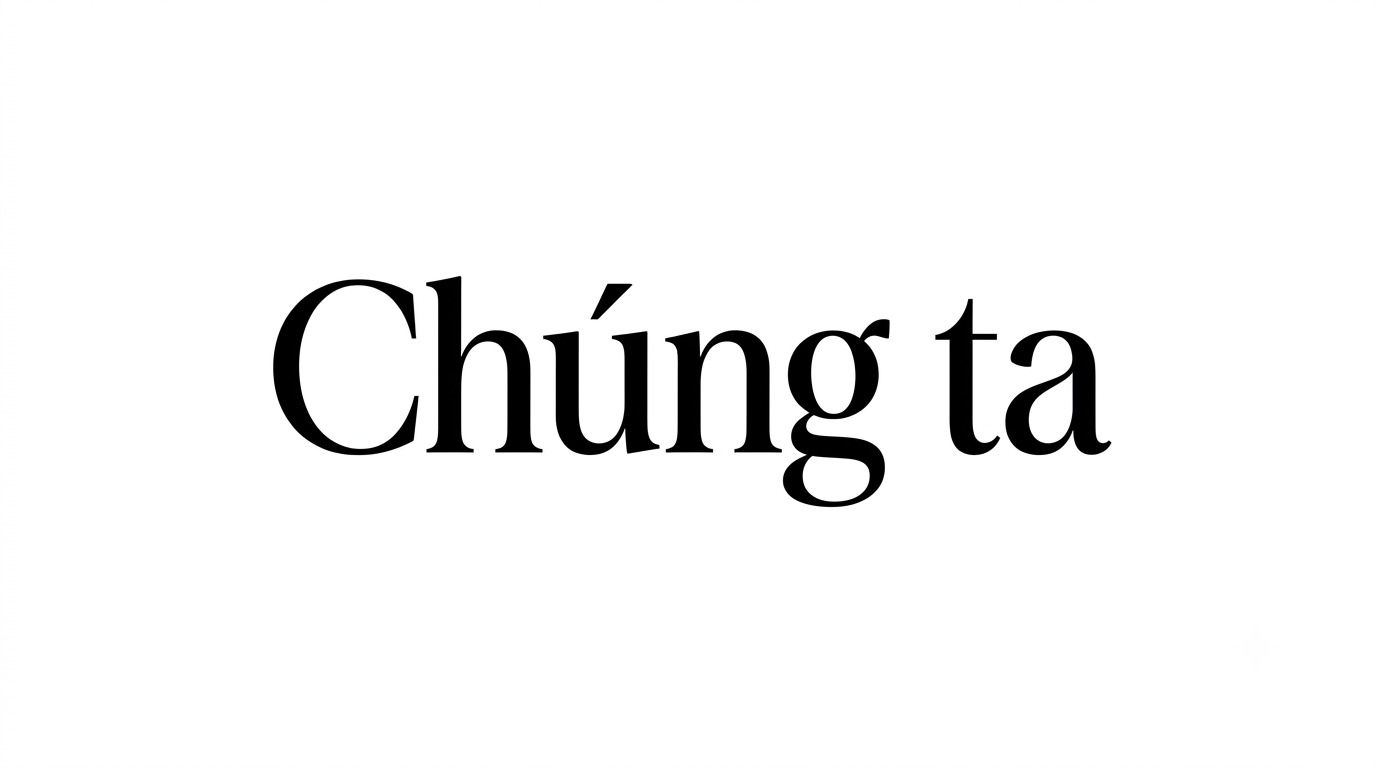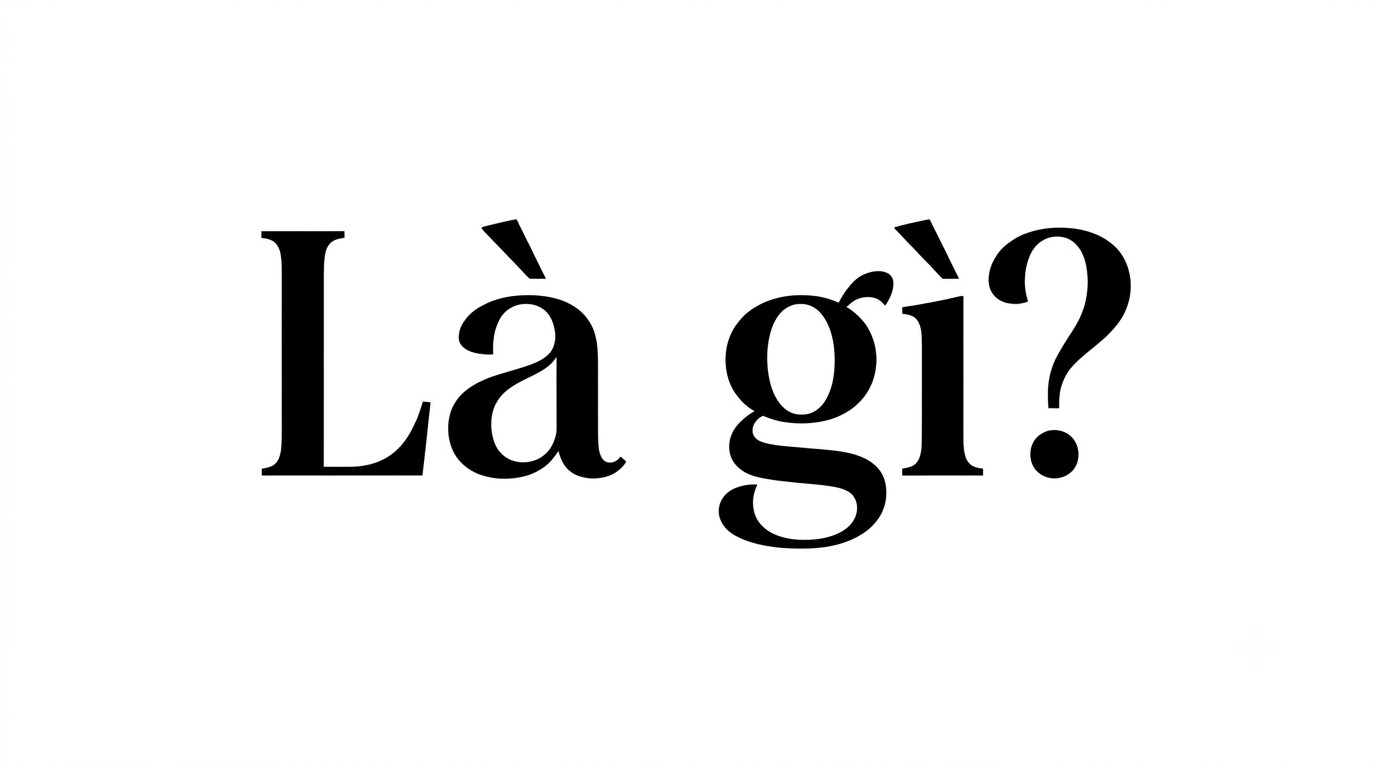
Tải 10+ bộ font Việt hóa Boxroom sắc nét chuyên cho thiết kế thương hiệu hiện đại
Nhiều nhà thiết kế yêu thích phong cách tối giản của Boxroom nhưng thường gặp lỗi font bị thiếu dấu tiếng Việt, sai ký tự hoặc đường path bị vỡ khi phóng lớn để in ấn hộp quà cao cấp. Những lỗi kỹ thuật này có thể làm giảm độ sắc nét của thiết kế, ảnh hưởng đến hình ảnh chuyên nghiệp và giá trị cảm nhận của thương hiệu.
Font Boxroom là gì?
Boxroom là một bộ phông chữ thuộc dòng Sans-serif hiện đại, gây ấn tượng mạnh mẽ nhờ cấu trúc hình học (geometric) cực kỳ gọn gàng và tinh tế. Đặc trưng của Boxroom là những đường nét thẳng dứt khoát kết hợp cùng các góc bo tròn nhẹ nhàng, gợi lên cảm giác về sự vững chãi nhưng vẫn rất ấm cúng và gần gũi. Đây là phông chữ lý tưởng cho các dự án nhận diện thương hiệu nội thất, bao bì công nghệ, nhãn hàng thời trang tối giản hoặc các ấn phẩm văn phòng của tập đoàn.
Trong thế giới đồ họa đương đại, xu hướng “Less is More” đang chiếm ưu thế, và Boxroom chính là “vũ khí” đắc lực để hiện thực hóa triết lý này. Tuy nhiên, phông chữ gốc thường không hỗ trợ các ký tự đặc thù của tiếng Việt như “đ, ư, ơ” hay hệ thống dấu thanh phức tạp. Bản font việt hóa Boxroom tại In Viva đã được căn chỉnh tỉ mỉ, đảm bảo các dấu thanh không bị dính nét và giữ nguyên được tỉ lệ vàng của bộ chữ gốc, mang lại trải nghiệm thị giác tuyệt vời trên mọi ấn phẩm in ấn.
Font Boxroom đẹp 01
Lưu ý: Với cấu trúc chữ hiện đại của Boxroom, bạn nên ưu tiên sử dụng các dải màu đơn sắc (Monochrome) hoặc các tông màu trầm để tôn vinh tối đa vẻ đẹp kiến trúc của bộ phông này trên bao bì sản phẩm.
5 ứng dụng của font Boxroom trong thiết kế và in ấn
Vẻ đẹp tối giản và hiện đại của Boxroom giúp tạo điểm nhấn chuyên nghiệp cho nhiều ấn phẩm quà tặng doanh nghiệp khi kết hợp cùng các kỹ thuật in ấn và gia công tại Xưởng In Viva:
• Thiết kế bao bì thiết bị điện tử và sản phẩm công nghệ: Boxroom phù hợp để in tên thương hiệu, mã sản phẩm hoặc thông tin kỹ thuật trên hộp cứng đựng tai nghe, sạc dự phòng, phụ kiện thông minh. Cấu trúc chữ gọn gàng giúp bao bì thể hiện sự chính xác và hiện đại.
• Sản xuất bộ quà tặng văn phòng in logo: Logo sử dụng font Boxroom khi in UV trên bình giữ nhiệt kim loại, sổ tay da hoặc khắc laser trên phụ kiện văn phòng tạo cảm giác tối giản, tinh tế, phù hợp với các dòng quà tặng dành cho đối tác và doanh nhân trẻ.
• In ấn túi giấy thương hiệu kiến trúc và nội thất: Phong cách chữ mạnh mẽ, cân đối của Boxroom phù hợp để thể hiện tên thương hiệu, slogan trên túi giấy Ivory hoặc giấy mỹ thuật, giúp bộ nhận diện giữ được sự đồng nhất và chuyên nghiệp.
• Trang trí bảng hiệu, backdrop và showroom: Với định dạng vector, font Boxroom có thể được phóng lớn để sử dụng trên bảng hiệu, khu vực trưng bày hoặc backdrop sự kiện mà vẫn giữ được đường nét rõ ràng, hạn chế tình trạng vỡ nét khi in kích thước lớn.
• Sản xuất tem nhãn decal sản phẩm: Nhờ cấu trúc chữ dễ đọc, Boxroom phù hợp để trình bày thông tin sản phẩm, thành phần hoặc mã nhận diện trên tem nhãn có kích thước nhỏ, giúp nội dung hiển thị rõ ràng hơn.
Font Boxroom đẹp 02
5 lưu ý khi sử dụng font Boxroom
Để thiết kế sử dụng font Boxroom đạt độ sắc nét và phù hợp khi đưa vào sản xuất thực tế, designer cần chú ý các yếu tố kỹ thuật sau:
• Điều chỉnh khoảng cách ký tự (Kerning): Boxroom có cấu trúc chữ hình học với các cạnh khá rõ nét. Khi sử dụng cho logo hoặc tiêu đề, bạn nên tinh chỉnh khoảng cách giữa từng ký tự để bố cục cân đối, đặc biệt khi in trên các bề mặt cong như bình giữ nhiệt, ly sứ.
• Tối ưu đường Path cho gia công bế nổi: Khi thực hiện dập nổi logo bằng font Boxroom trên hộp cứng, file thiết kế cần được xử lý các điểm neo và góc cạnh trong đường vector. Việc này giúp khuôn dập tái hiện chữ chính xác hơn, hạn chế tình trạng rách mép giấy hoặc mất chi tiết nhỏ.
3. In Viva có hỗ trợ thiết kế bao bì sử dụng font Boxroom không?